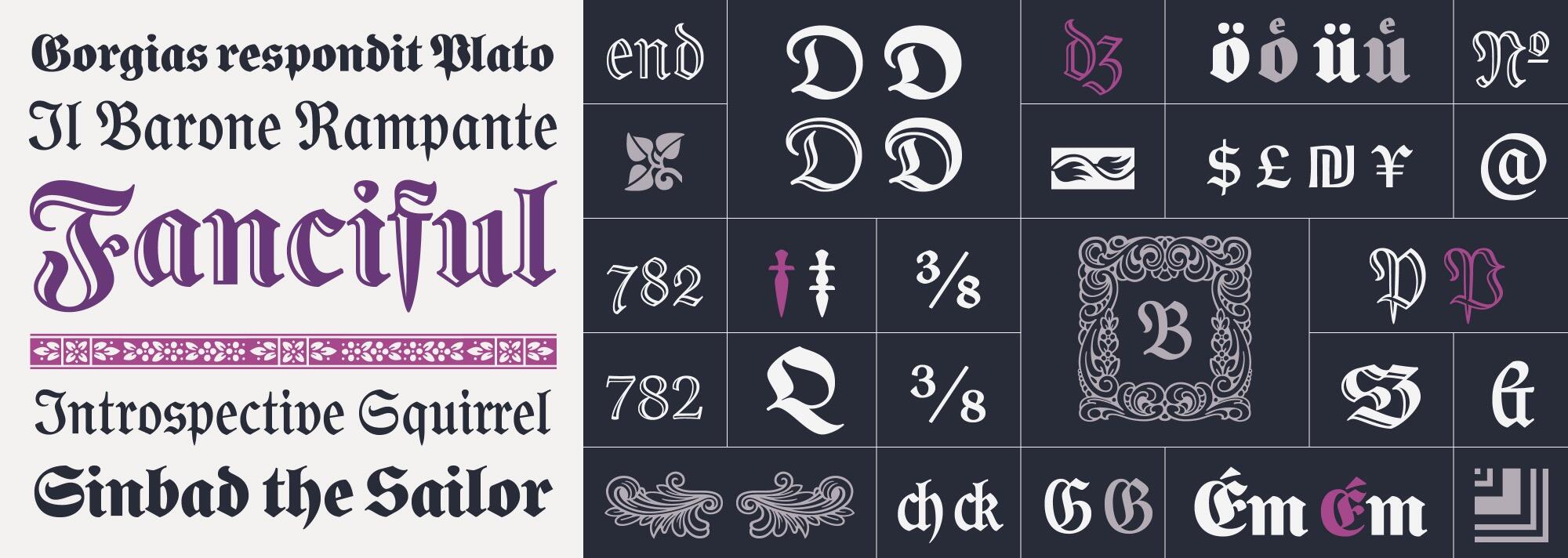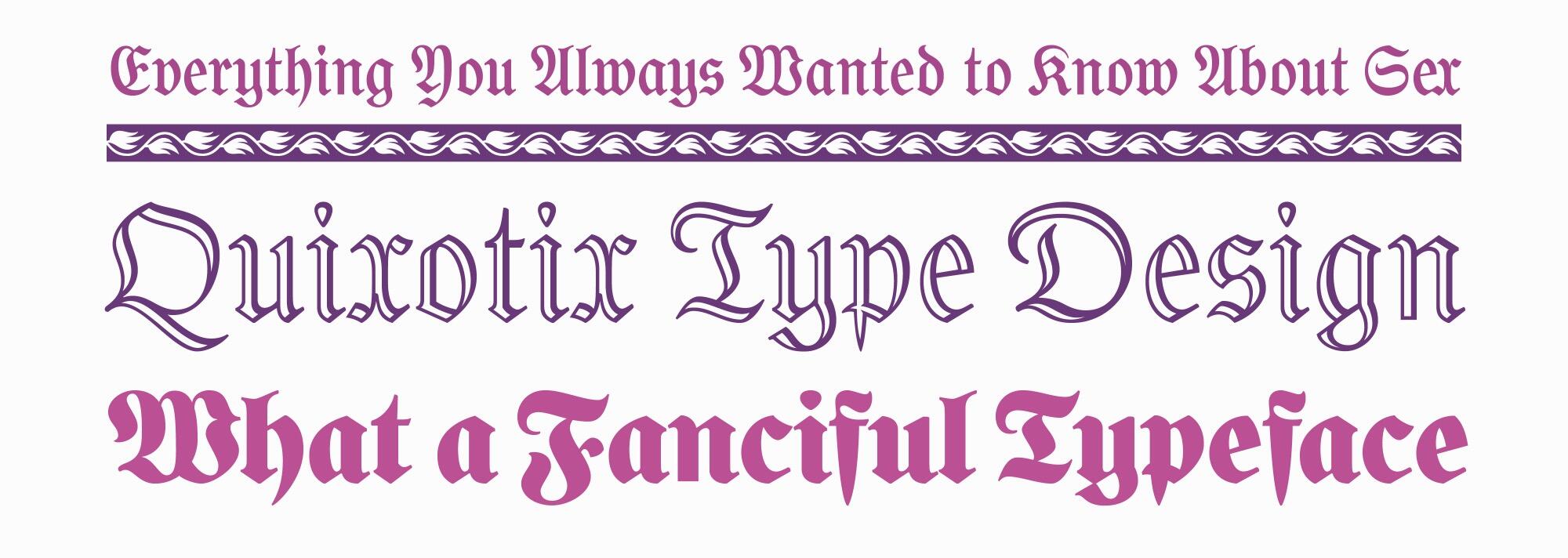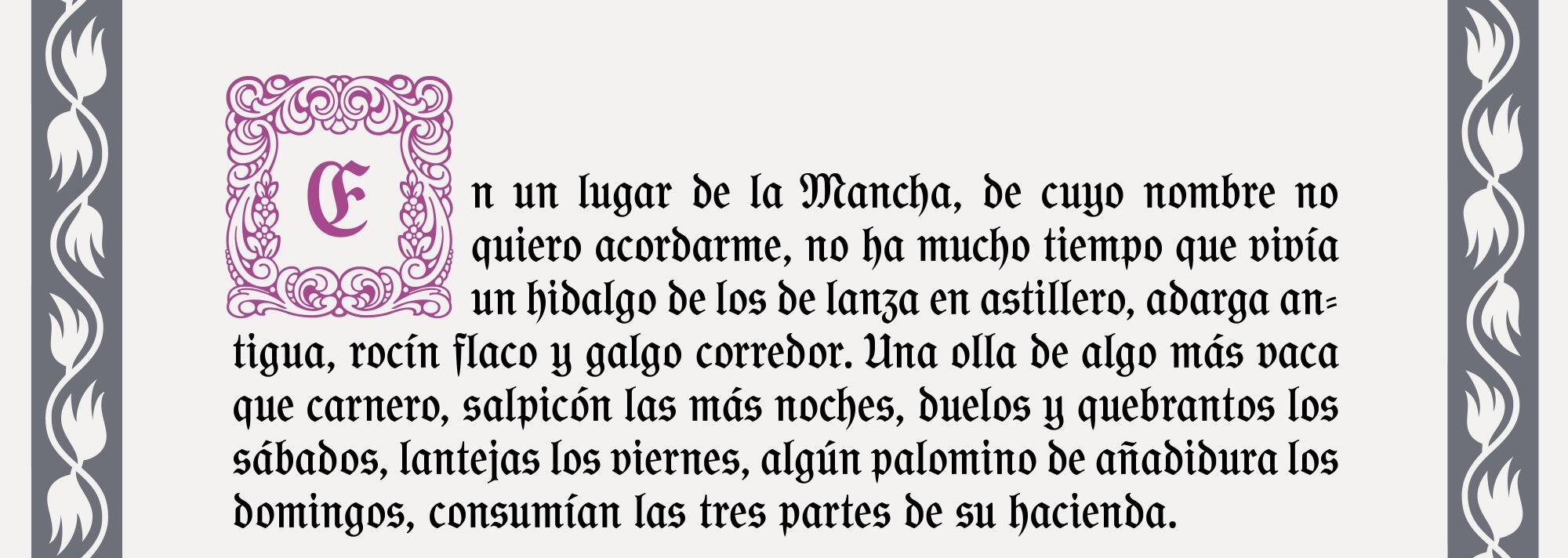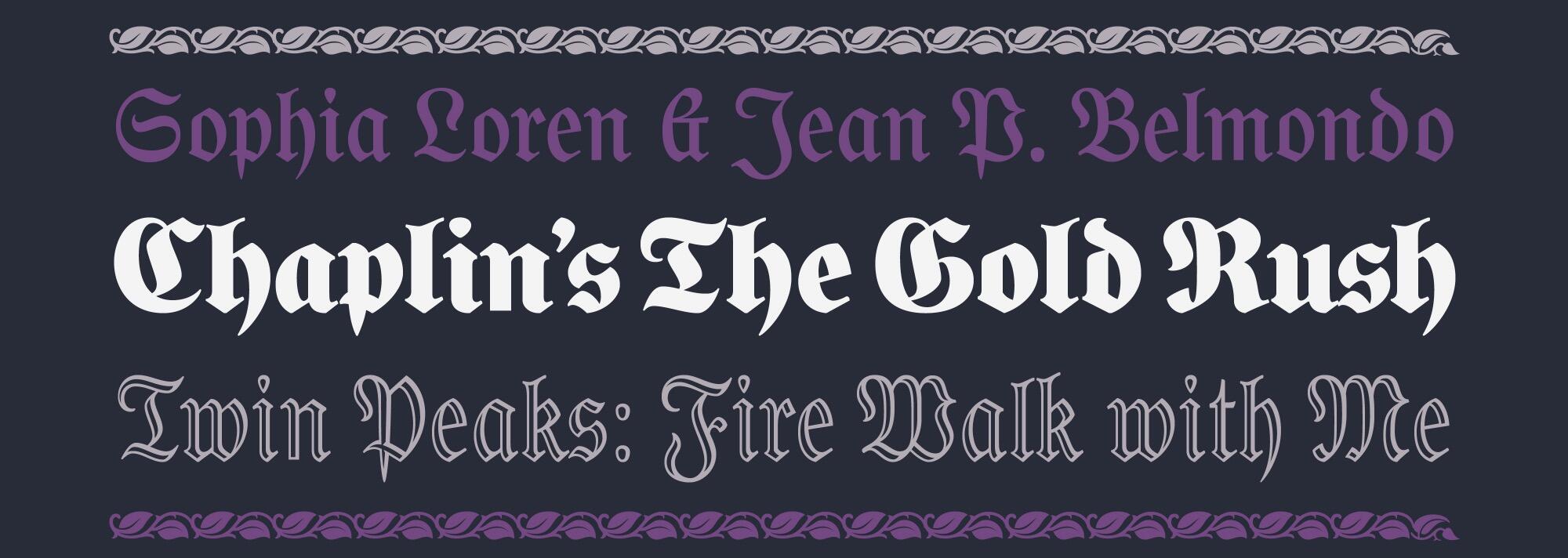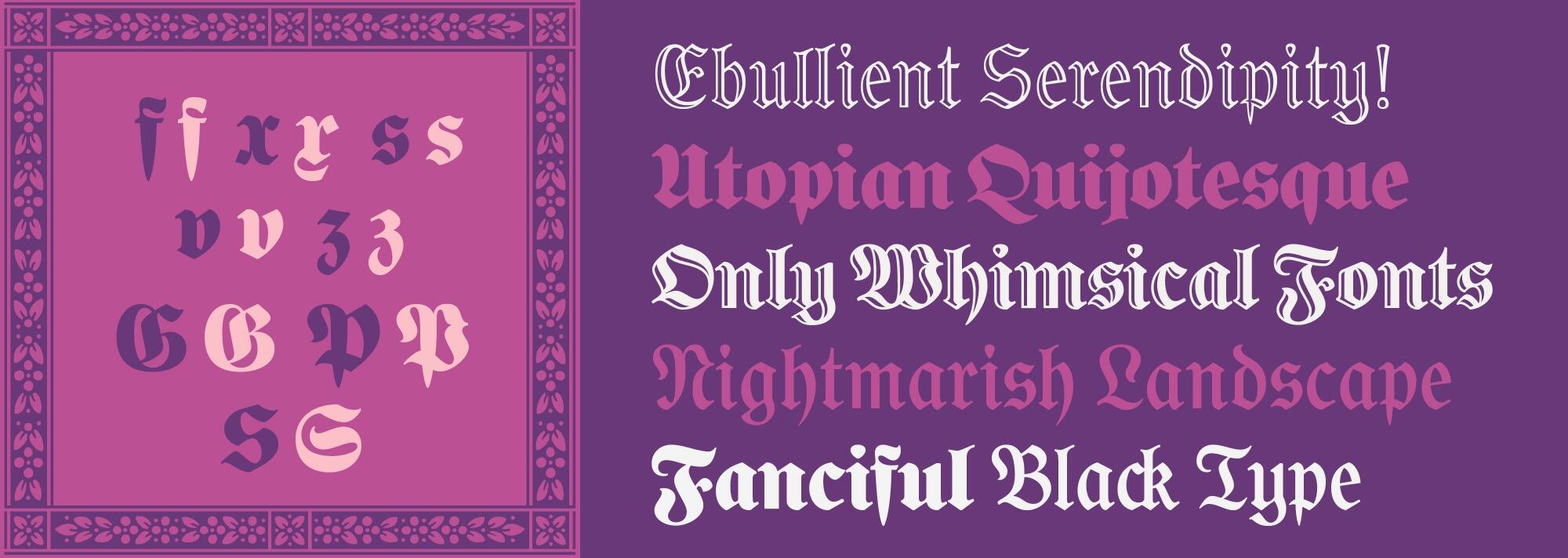
- Gebrochene Schrift
- Versaleszett:
- enthalten
Ausgangspunkt für diese Schrift von José Manuel López Rocha war ein deutsches Fraktur-Buch mit dem Titel »Platos Gorgias« aus dem Jahr 1911. Die daraus abgeleitete digitale Schrift wurde in vier Schnitten ausgebaut: davon zwei Strichstärken, jeweils in normaler und lichter Version. Der Zeichenvorrat ist für die Digitalisierung einer gebrochenen Schrift ungewöhnlich groß. Die Schnitte erlauben einerseits traditionellen deutschen Fraktursatz mit allen optionalen und obligatorischen Ligaturen und Varianten für deutsche Umlaute mit hochgestelltem e. Daneben ist ein moderner bzw. internationaler Einsatz ebenfalls möglich. Für die typischen Frakturformen gibt es Alternativzeichen im Antiqua-Stil. Es gibt mehrere Ziffernsets (einschließlich Brüchen), hoch- und tiefgestellte Zeichen, viele Währungszeichen, eine erweitere lateinische Belegung, Schmuckzeichen, Rahmenelemente und Initialen. Selbst ein großes Eszett als SZ-Ligatur ist enthalten.